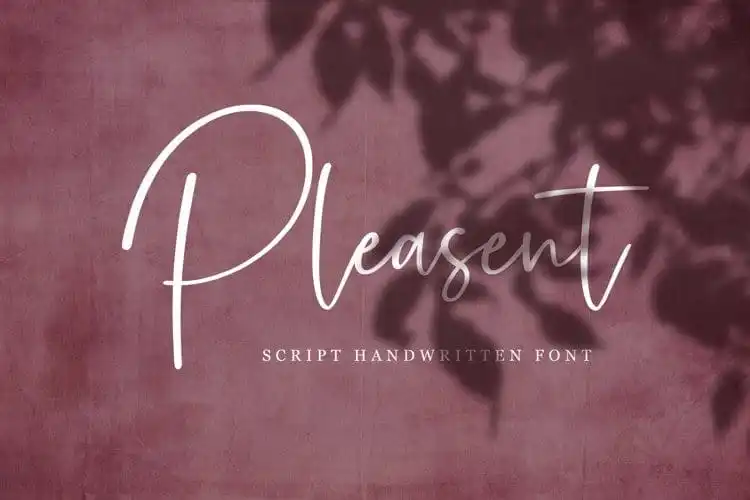
Pleasent Script Font
A nova fonte script “Pleasent Script Font” do Dav Studio vem trazer uma dose agradável de elegância ao seu design. Perfeita para quem busca misturar o estilo clássico com a chamada moderna, essa fonte oferece um toque refinado que combina arquitectura e criatividade na mesma peça. Ideal para business cards, convites de casamento, logomarcas, ilustrações e todas as suas necessidades criativas, ela é uma mistura perfeita entre escrita manual com um brilho chamadista de arte filigrânica. Essa fonte não apenas revolucionará seu design, mas também deixará sua marca única em qualquer projeto. Seja para personalizar o layout de sua identidade visual ou criar um sentido de espírito único e atraente para suas campanhas publicitárias, “Pleasent Script Font” é uma escolha estratégica que vai fazer toda a diferença.